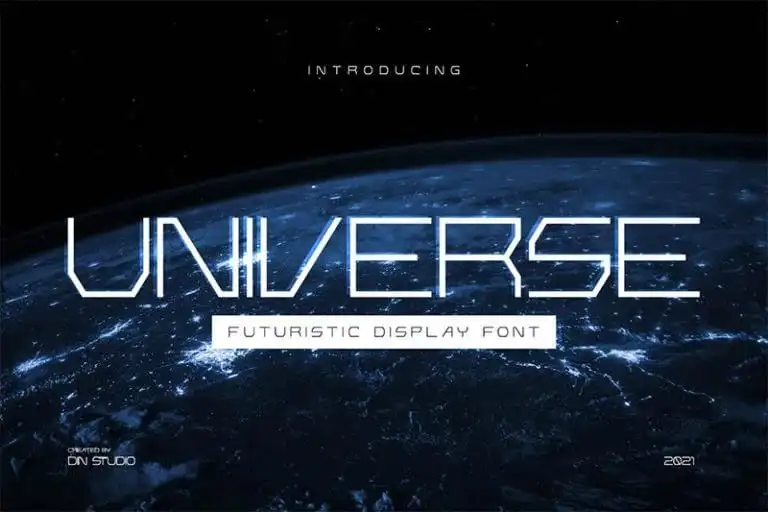
Universe Display Font – Download Grátis
Introduzimos a fonte “Universe Display Font”. Essa fonte é estilosa e versátil, com linhas retas e desenho alongado que enfatiza a criatividade e individualidade. Foi criada pelo design de fontes Din Studio. Este tipo de letra com estilo futurista tem um visual interessante para uma variedade de projetos e promoções. É perfeito para ser usado em sua web, branding no seu perfil nas redes sociais, banners na Pinterest, produtos impressos e muito mais!